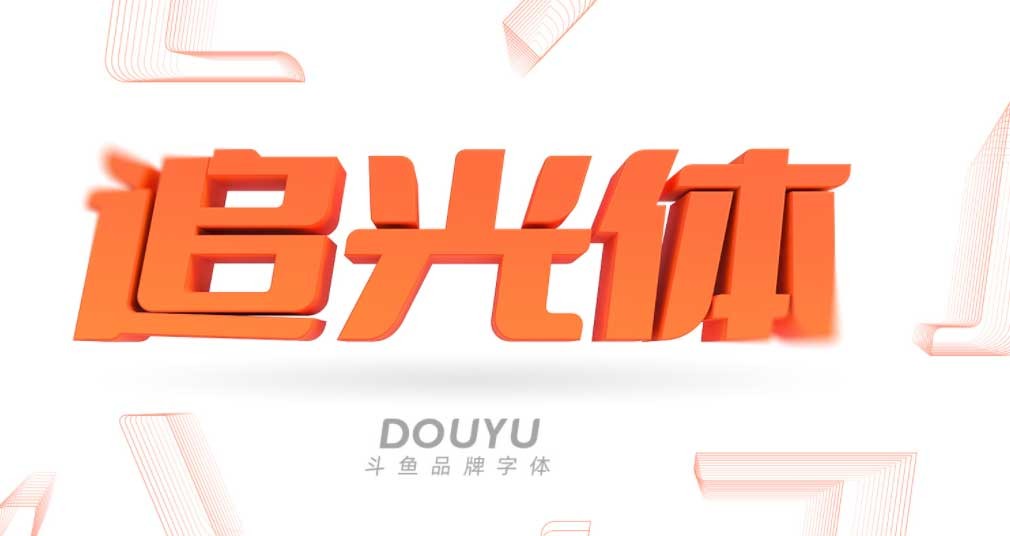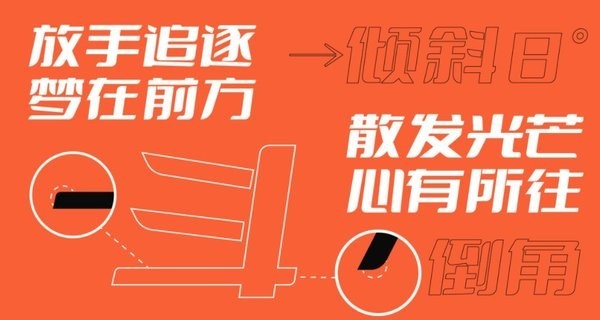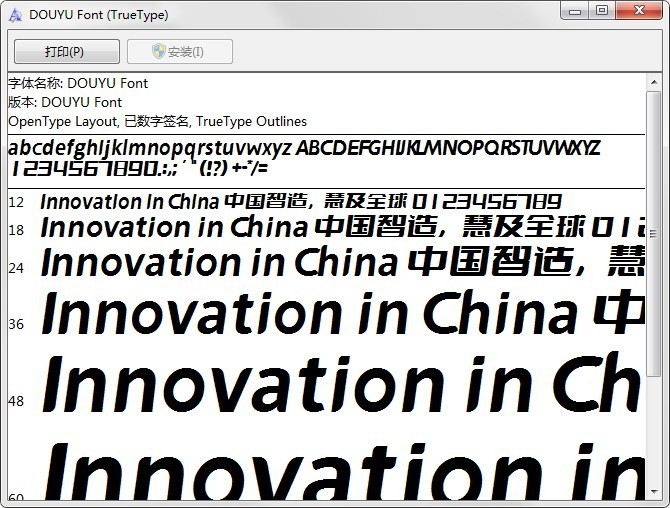
斗魚追光體免費(fèi)商用版是一款斗魚旗下設(shè)計的個性藝術(shù)字體,可以用于商用或者個人、企業(yè)免費(fèi)使用,適用范圍十分廣泛,廣告設(shè)計、海報設(shè)計、包裝設(shè)計等都能使用。還蘊(yùn)涵獨(dú)特意義,表達(dá)勇往直前、追逐夢想,向前沖的情感,喜歡的伙伴們可不要錯過!
斗魚追光體,是由斗魚武漢研發(fā)部UED提供指導(dǎo),品牌組設(shè)計成員主導(dǎo)設(shè)計的全新品牌字體。是符合GB2312簡體中文編碼字符標(biāo)準(zhǔn)的專屬品牌字體。是擁有一種標(biāo)準(zhǔn)版字重,包含6763個中文字符,100個西文及數(shù)字符號。隨著斗魚品牌場景的日益豐富,斗魚追光體能逐漸適配平臺的各種場景。
-- 文字呈現(xiàn)右傾斜,代表著一種勇往直前、奔跑沖向夢想的含義
-- 可以用于影視、廣告、包裝等等領(lǐng)域